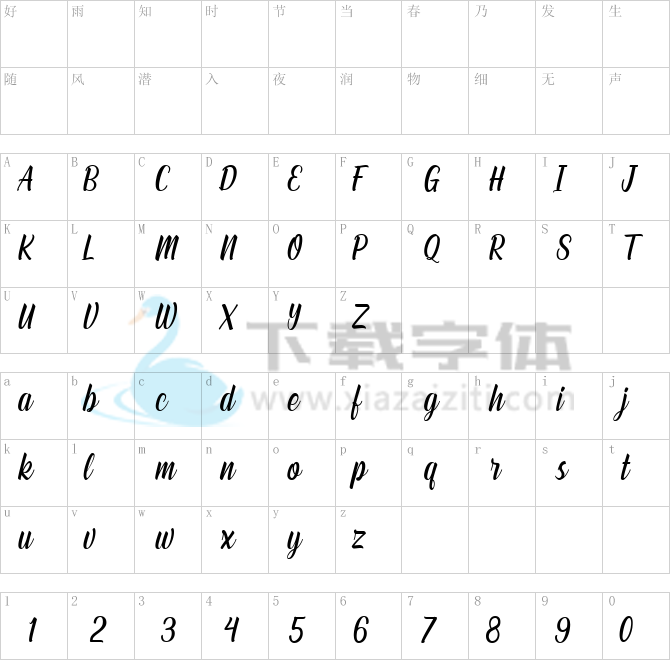
Auntie.ttf字体下载,这款字体结构工整、笔画清晰,兼顾美观与易读性,适用于标题、正文、海报、包装、LOGO 等多种场景。字形优雅稳定,风格百搭耐看,适配日常排版与创意设计,让文字呈现更舒适、更具质感。Auntie.ttf字体下载一笔一画,皆是细节,以均衡的比例、流畅的线条打造舒适视觉体验,字形端正大气,风格简约现代。无论是商业设计、品牌宣传还是日常排版,都能轻松驾驭,让文字更有格调与力量。Auntie.ttf字体下载字体下载。